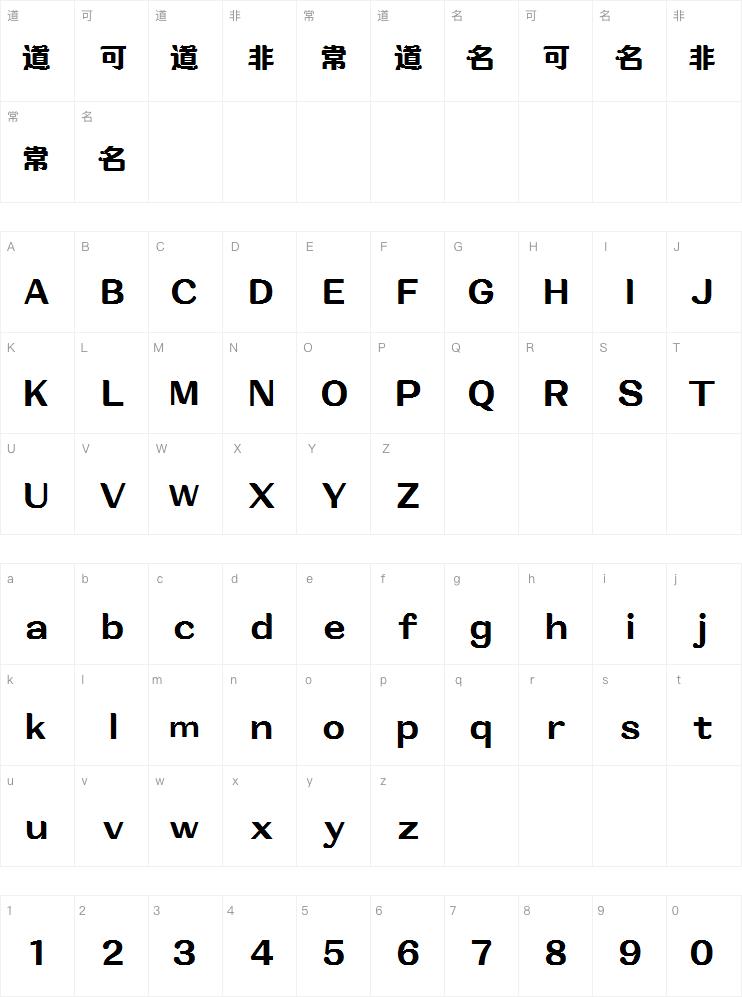
字魂海昌海洋
字魂海昌海洋体是字魂为海昌海洋工作以以“字愈海洋”为主题推出的定制字体。这款字体的设计灵感源于对海洋生态的有机解构。设计团队收集了人们心目中的海洋关键词,将海浪造型、海洋生物线条转译到字体一笔一画之中。而笔画重叠处的剪切留白,既赋予字体宛如潮汐般透气感,又暗合 “人类与海洋同呼吸、共命运” 的生态关联。这种设计不仅具有独特的视觉美感,更在当代的各种应用场景,如广告设计、海报制作、文化宣传等领域中,展现出强大的适应性。